Как универсальный шрифт, который станет самым востребованным в мире, создается с помощью краудсорсинга
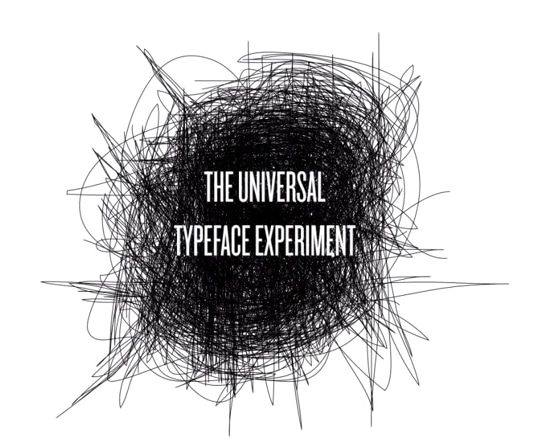
Краудсорсинг – это способ сбора информации, идей и контента с помощью большого числа участников. Это также отличный способ дать людям ощущение причастности к чему-то значимому, в то время как ваша компания имеет возможность собрать нужные данные и прорекламировать свои товары или услуги.
Для того чтобы отпраздновать выпуск 100 миллиардов ручек и анонсировать новую ручку-стилус Cristal pen, компания BiC решила запустить проект Universal Typeface по созданию универсального рукописного шрифта, где каждый участник внесет свой вклад в конечный результат.
Был создан специальный сайт, на котором любой желающий может принять участие в кампании, написав буквы латинского алфавита. На сайте также есть возможность просмотреть результаты людей по всему миру. Участники проекта общими силами создадут новый шрифт «Universal Typeface», который будет анонсирован в августе 2014 года.
Несмотря на то, что в наш цифровой век мы все меньше пишем от руки, остается большое количество людей, для которых такой способ письма остается предпочтительным.